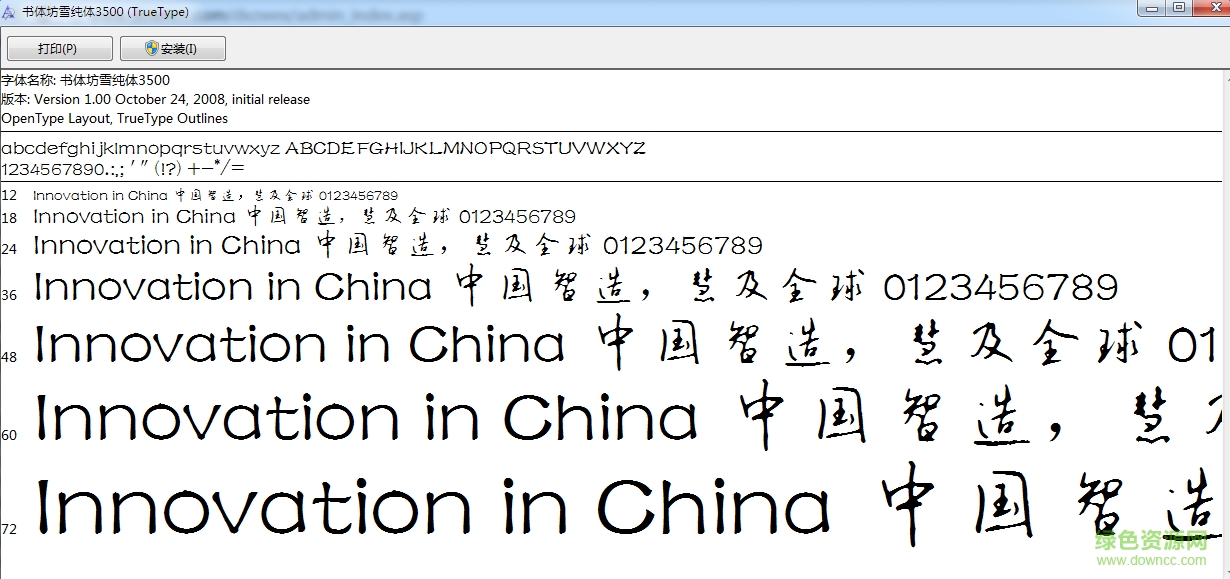
書體坊雪純體3500字體是一款根據(jù)手寫字體制作的電腦字體,本款字形端正又瀟灑,外觀非常美觀,可適用于簽名設(shè)計(jì)、廣告設(shè)計(jì)等,有需要的朋友歡迎下載使用!
書體坊雪純體3500是一款特別漂亮的手寫字體,收錄有3500個(gè)常用的漢字,一些個(gè)人署名、個(gè)人簽名等都可以使用到這款字體哦。